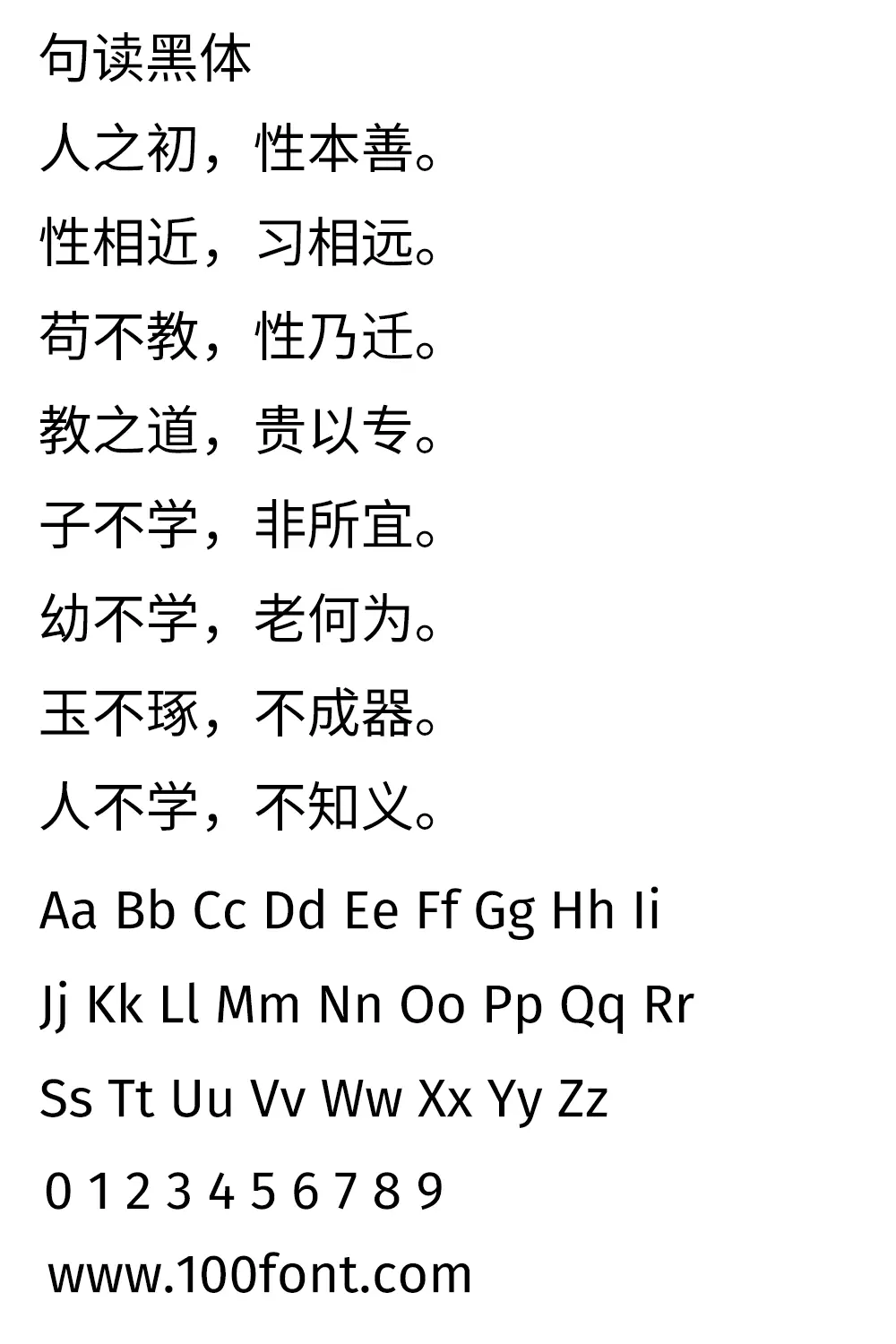
句讀黑體,支持多種語言文字的商用免費開源黑體,基於更紗黑體、思源黑體、尙古黑體、Noto Traditional Nushu、KhaWa Sans 和 FiraGO。
支持的文字:漢字、假名、諺文、女書、藏文、拉丁文擴展、西里爾文擴展 (包含塞爾維亞語和保加利亞語的 Opentype locl 特性)、希臘文擴展、國際音標、阿拉伯文、天城文、格魯吉亞文、希伯來文、泰文。